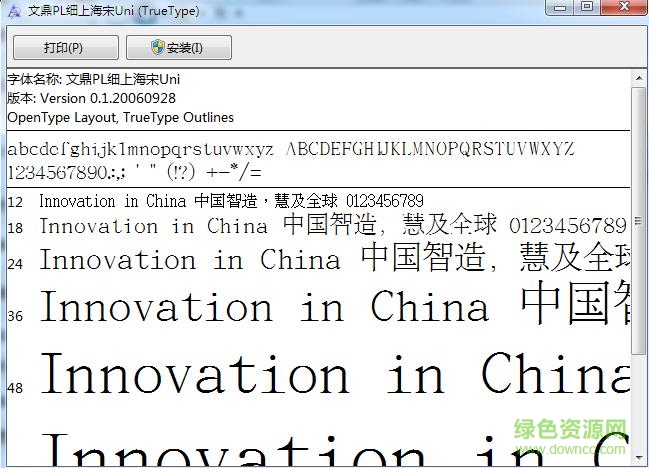
文鼎細(xì)上海宋是一款根據(jù)經(jīng)典的宋體字體打造的電腦字體,字形清晰大方得體,筆畫(huà)結(jié)構(gòu)十分對(duì)稱,非常適合用作標(biāo)題或者是的進(jìn)行平面設(shè)計(jì),有需要的朋友歡迎下載使用!
文鼎細(xì)上海宋是文鼎字體打造的一款獨(dú)具風(fēng)格的宋體字體,字體效果比較簡(jiǎn)單清爽,給人非常舒服的感覺(jué),深受廣大年輕人的喜愛(ài)!